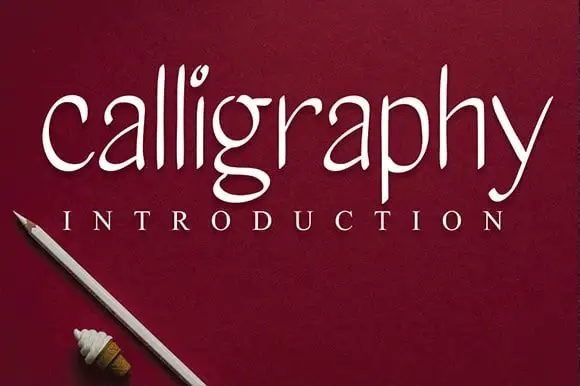
A Calligraphy Script Font é uma criação criativa que se destaca na categoria de Handwritten Fonts, ideal para diversos projetos que valorizam a escrita manual. Este estilo elegante e sofisticado foi desenvolvido pelo designer andikastudio, e seu impacto pode ser percebido em uma variedade de mídias digitais. Suas linhas fluidas e detalhes suaves tornam esta fonte perfeita para aplicativos em paredes, como desenhos de casamentos ou postagens sociais com logomarcas criativas. Ela também combina perfeitamente com as necessidades dos anúncios, embalagens de produtos, rótulos e até mesmo trabalhos de fotografia, incluindo watermarking. Através da Calligraphy Script Font, seus projetos podem ser ainda mais especializados e personalizados, proporcionando uma experiência visual única para os usuários do seu projeto. Com a Calligraphy Script Font, você pode transformar qualquer projeto em algo único, cheio de estilo e personalidade.